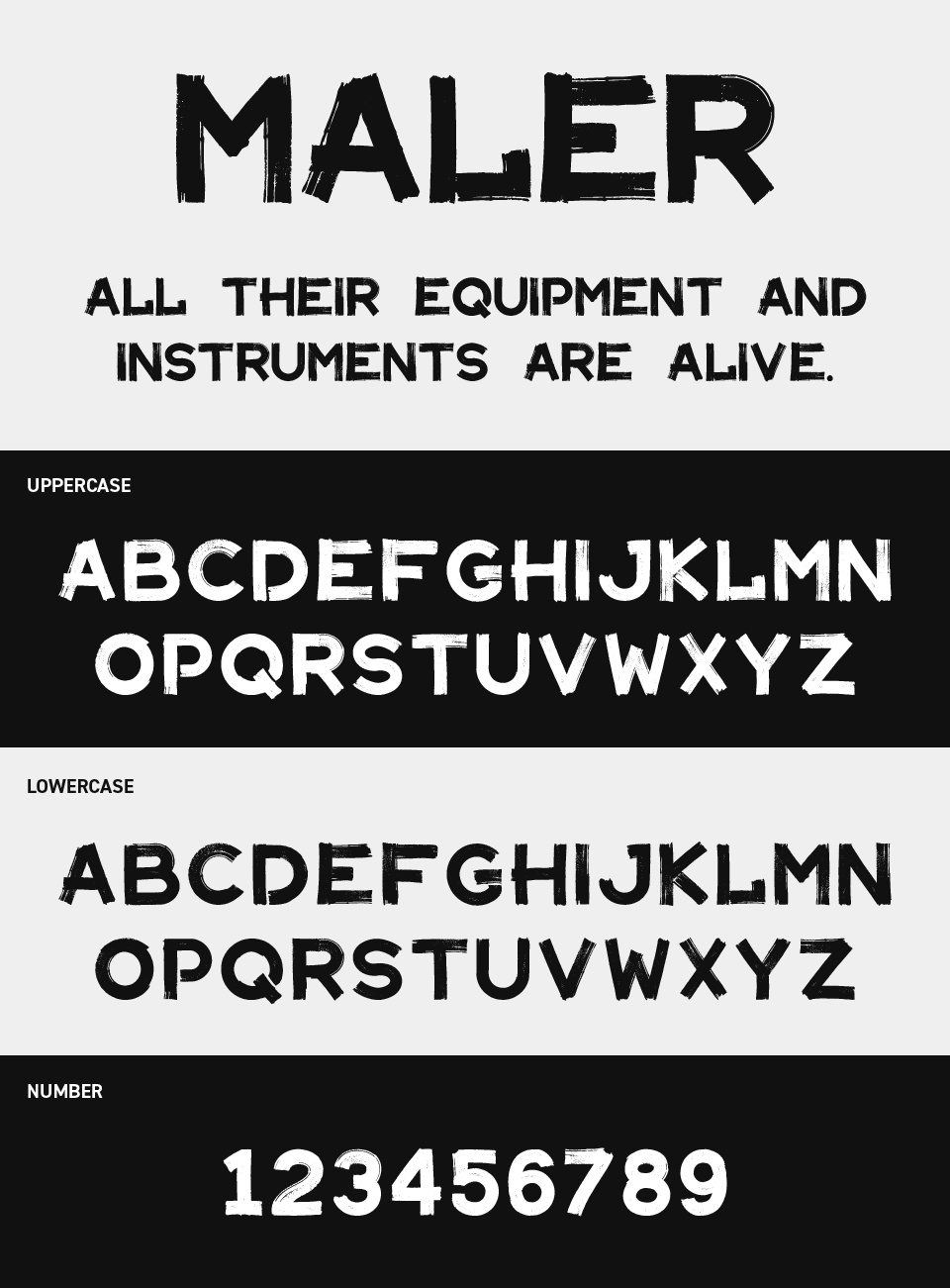
MALERフォントは、太い筆でざっくり描いたような勢いのあるタッチが楽しい、手描き風のゴシック体フォントです。かすれや重なりの表情がところどころに現れていて、まるでアトリエの壁に即興で描かれた文字のような雰囲気があります。
少し無造作だけど、そこがちょうどいい。きっちりしすぎず、ちょっとラフで自由な印象があり、アートイベントのタイトルや、個性的なPOPなどに使いたくなるような、元気のあるフォントです。